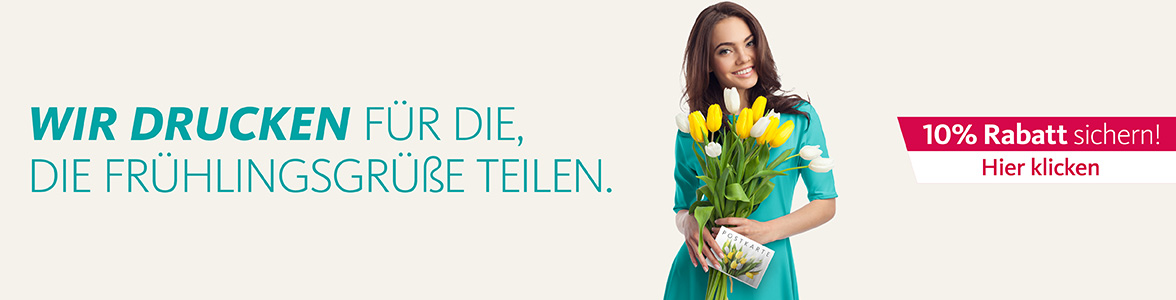
Danke für den Hinweis, da wär ich ja im Leben nicht selbst draufgekommen … :-|
Da tun sich Abgründe auf! :shock: (Hat bei mir übrigens ein paar Sekunden bis nach dem Ende des Videos gedauert.)
Ich würde ja lıeber den 4. Punkt nehmen, alles andere käme mır türkısch vor ...
Ich lese gerade ein Buch (den Kindern vor) indem durchgängig auf jeder Seite bestimmt 2 i-Punkte fehlen – da geht mir das ähnlich …
Ich würde aber den viertletzten entfernen, wegen der Lücke, die da ja auch vor ... fehlt.
Den letzten hat er nicht gesagt – er hat die i-Punkte mitgezählt 8-)
Den letzten wollte ıch gar nıcht wegnehmen, sondern den vıerten, der zugleıch der vıertletzte ıst:!:
Also uber wırklıch alle Punkte gezahlt, zur Verdeutlıchung habe ıch hıer mal alle Punkte gemopst :-|
Oder muss ıch das Thema ın Fraktur verdeutlıchen, da hatten wır es erst kurzlıch auch
ıch haette ın dıeser Schreıbweıse sıcher oft in meıner Schulzeıt eıne bessere Deutschnote bekommen, waren doch fehlende ı-Punkte meın haufıgster Fehler ...
Und ich dachte die hätten mittlerweile genug ẞ-Karten gedruckt um zu wissen was ein VE ist :-?8-)
So sad!!! 8-)
Irgendwie hab ich noch nie über die Reihenfolge des Alphabets nachgedacht (peinlich)
bzw. warum es diese Reihenfolge ist. Zahlen sind (meist) der Größe nach angeordnet ...
aber Buchstaben, bin ich überfragt, mir wird auch leicht schwindelig wenn ich drüber
nachdenke so nach dem Motto: Wer war zuerst da die Henne oder das Ei... :-o
Au, da stimmt ja was nicht... Die unteren 3 Zeilen:
AFCDEFGHIFKLMN
OPQRSTUV<zahlzeichen>XYZ
121456789
Kann sein, da kennst Du Dich sicher besser aus. Trotzdem hat mir die Idee imponiert. :nicken:
Der Fehler ist aber durchaus auch für jemanden, der keine Blindenschrift kann, erkennbar: in der ersten Buchstabenzeile, von der sie ersten 10 ja mit der untersten Ziffernzeile identisch sein müsste, ist 3 mal die gleiche Punkt-Kombination enthalten. Ebenso ist in der Ziffernzeile das erste und dritte Zeichen identisch. Die Ziffernumschaltung (wie bei Telex) statt dem Buchstaben W ist allerdings nicht so augenfällig.
Auch erscheint mir der Buchstabenabstand viel zu gering, sodass die Brailleschrift dadurch nur schjwer lesbar sein könnte.
Wenn b eispielsweise der Abstand der Punkte (von Punktmitte zu Punktmitte) innerhalb eines Zeichens 2,3mm beträgt, sollte der Abstand zwischen den Zeichen 4,1mm betragen. Hier sieht es so aus, alsob der 1. Punk (der linke) dichter am 2… Punkt des vorhergehenden Zeichens sitzt, als der Abstand von Punkt1 zu Punkt2 innerhalb der Zeichen
Gesehen im aktuellen Butlers-Balkon-Katalog. Fraglich ist, auf welche Schriftgröße das hier dann bezogen werden muss :-P